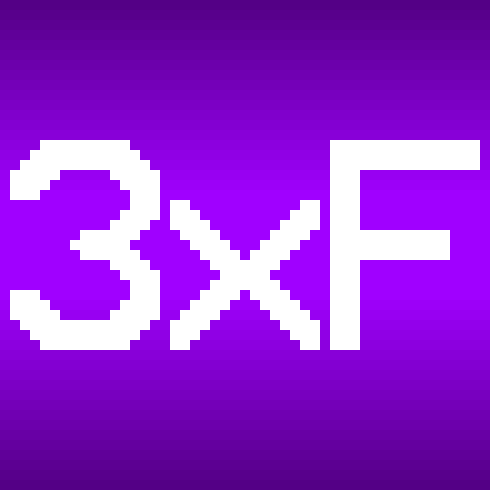
GUI Scale 3 Font
Стилизованный шрифт для тех, кто играет в Minecraft с масштабом интерфейса 3. Идеально подходит для 1080p мониторов, решая проблему размытых текстур при нестандартном разрешении.
GUI Scale 3 Font - это не просто шрифт, а спасение для всех, кто сидит на 1080p мониторах и мучается с настройками интерфейса в Майнкрафт. Давай честно: большинство геймеров до сих пор используют 1080p, будь то отдельный монитор или встроенный экран ноутбука. И тут возникает классическая проблема: какой масштаб интерфейса выбрать?
В чём соль?
Любой, кто хоть раз заглядывал в настройки видео в Minecraft, видел опцию GUI Scale. И если у тебя 1080p, то ты наверняка заметил: масштаб 3 выглядит лучше всего. Масштаб 2 - слишком мелко, глаза вытекают. Масштаб 4 - уже слишком крупно, экранного пространства почти не остаётся. Но вот загвоздка: если GUI Scale 3 - это идеал, то почему почти никто не делает ресурспаки под 48x?
Степени двойки против кратных 16
Короче, сообщество создателей ресурспаков для Minecraft подсело на степени двойки. Найти паки на 8x, 16x, 32x, 64x, 128x - легко. Но настройка GUI Scale в Майнкрафт работает не по степеням двойки, а по кратным 16.
Стандартные текстуры в игре - 16x16 пикселей. Когда ты меняешь масштаб интерфейса, ты выбираешь целое кратное от 16x для отображения меню, кнопок и текста.
• 1 × 16 = 16x - стандарт, всё привычно.
• 2 × 16 = 32x - вдвое больше деталей. Например, Faithful - классика.
• 4 × 16 = 64x - вчетверо больше. VanillaXBR - отличный пример.
Но мы пропустили один вариант. Мы же не Valve, считать умеем, правда?
3 × 16 = 48x. И хотя это отлично работает в игре, 48x получает смехотворно мало внимания от сообщества. Серьёзно, почти никто не делает паки на 48x. Раньше на Modrinth даже категории такой не было, что делало продвижение таких паков настоящим квестом. Но после декабря 2022 года ситуация исправилась - появился тег 48x. Спасибо разработчикам Modrinth за адекватную реакцию.
Зачем вообще нужен 48x пак?
Тут всё просто: Minecraft использует масштабирование по ближайшему соседу (nearest-neighbor), когда разрешение пака не совпадает с масштабом интерфейса. Стандартные 16x текстуры легко растягиваются до 32x, 48x или 64x - они же все кратные 16. Но что будет, если поставить 32x или 64x пак и включить GUI Scale 3?
Почему 32x пак не подходит
32x текстуры нельзя чисто растянуть до 48x. Появляются артефакты из-за нецелочисленного преобразования. Всё выглядит размыто и криво.
Почему 64x пак тоже не вариант
Переход с 64x на 48x - ещё хуже. Пиксели приходится выбрасывать, чтобы уменьшить изображение. В результате - ужасные артефакты. Текстуры выглядят так, будто их собака пережевала.
Наконец-то, 48x шрифт
Создавать целый 48x пак, перерисовывая каждую текстуру в игре - это навсегда. И это если не свихнуться в процессе. Поэтому я взял на себя задачу улучшить жизнь всех, кто использует GUI Scale 3, создав новый шрифт, который реально выглядит хорошо при этом масштабе.
Этот шрифт - не копия ванильного, а полная переработка по моему вкусу. И выглядит он в игре просто отлично.
Что уже сделано
На данный момент (версия 1.1) готов только базовый ASCII. В будущих версиях планируется поддержка символов с диакритикой и нелатинских европейских символов. Ещё хочу добавить забавную модификацию - замену SGA на английские символы.